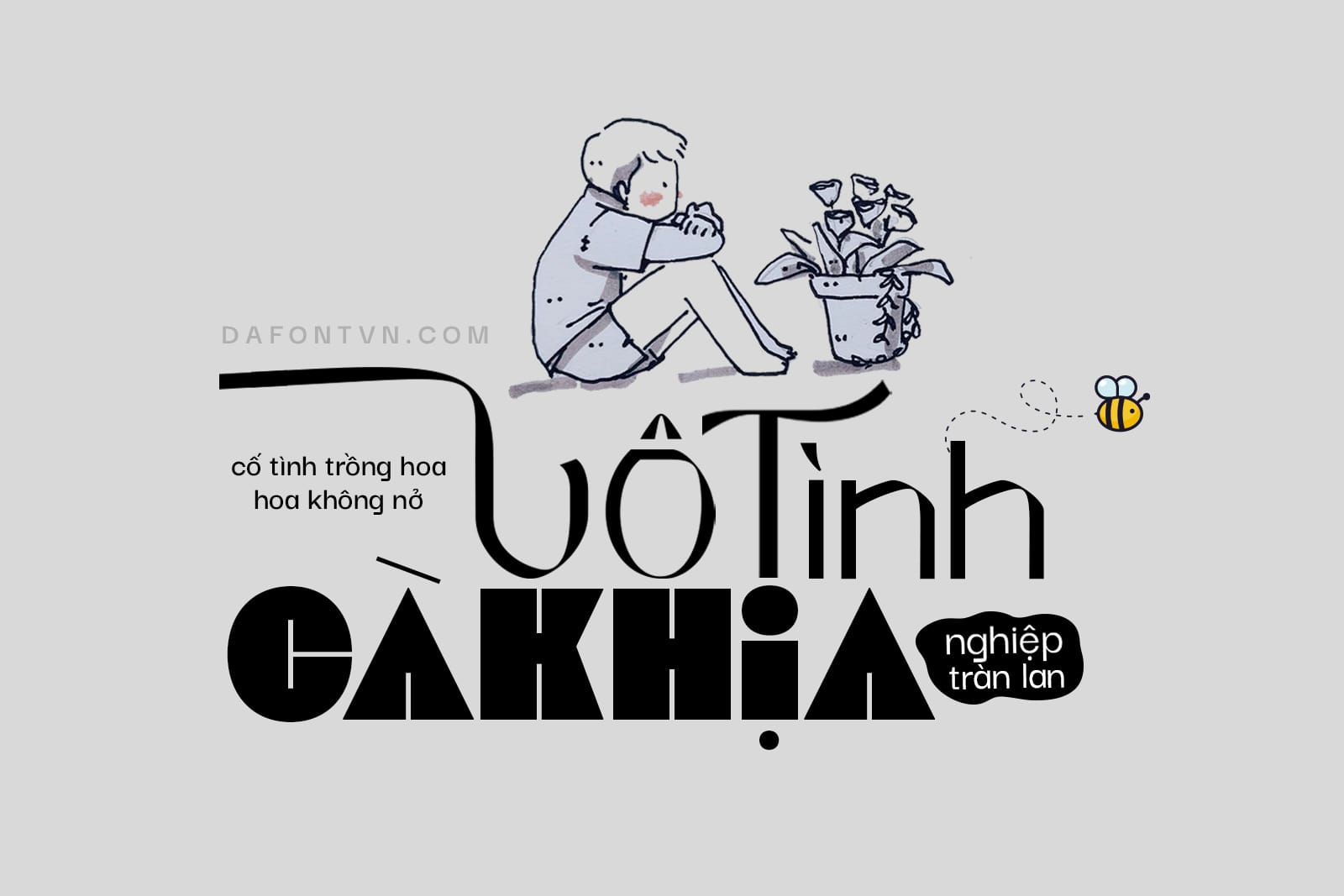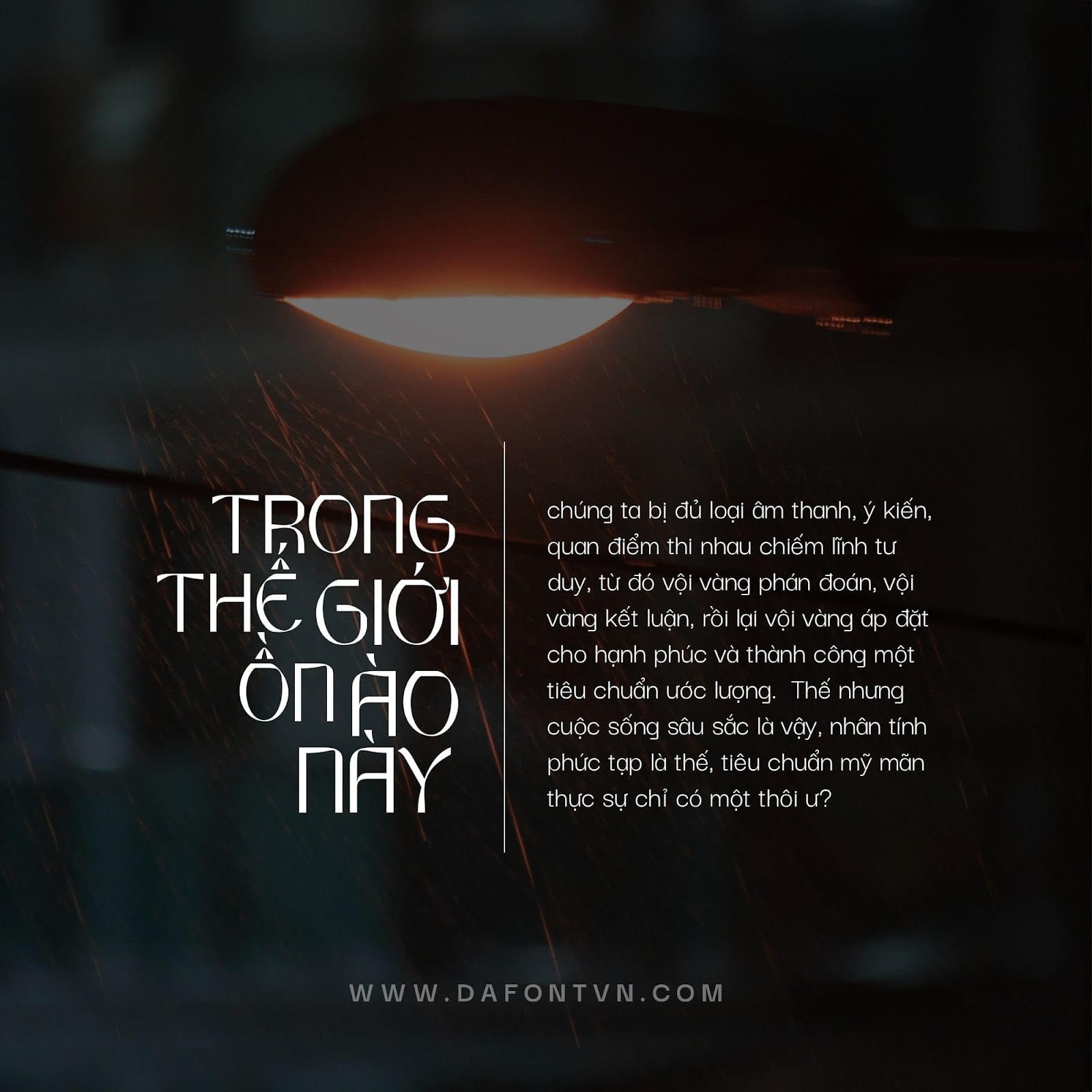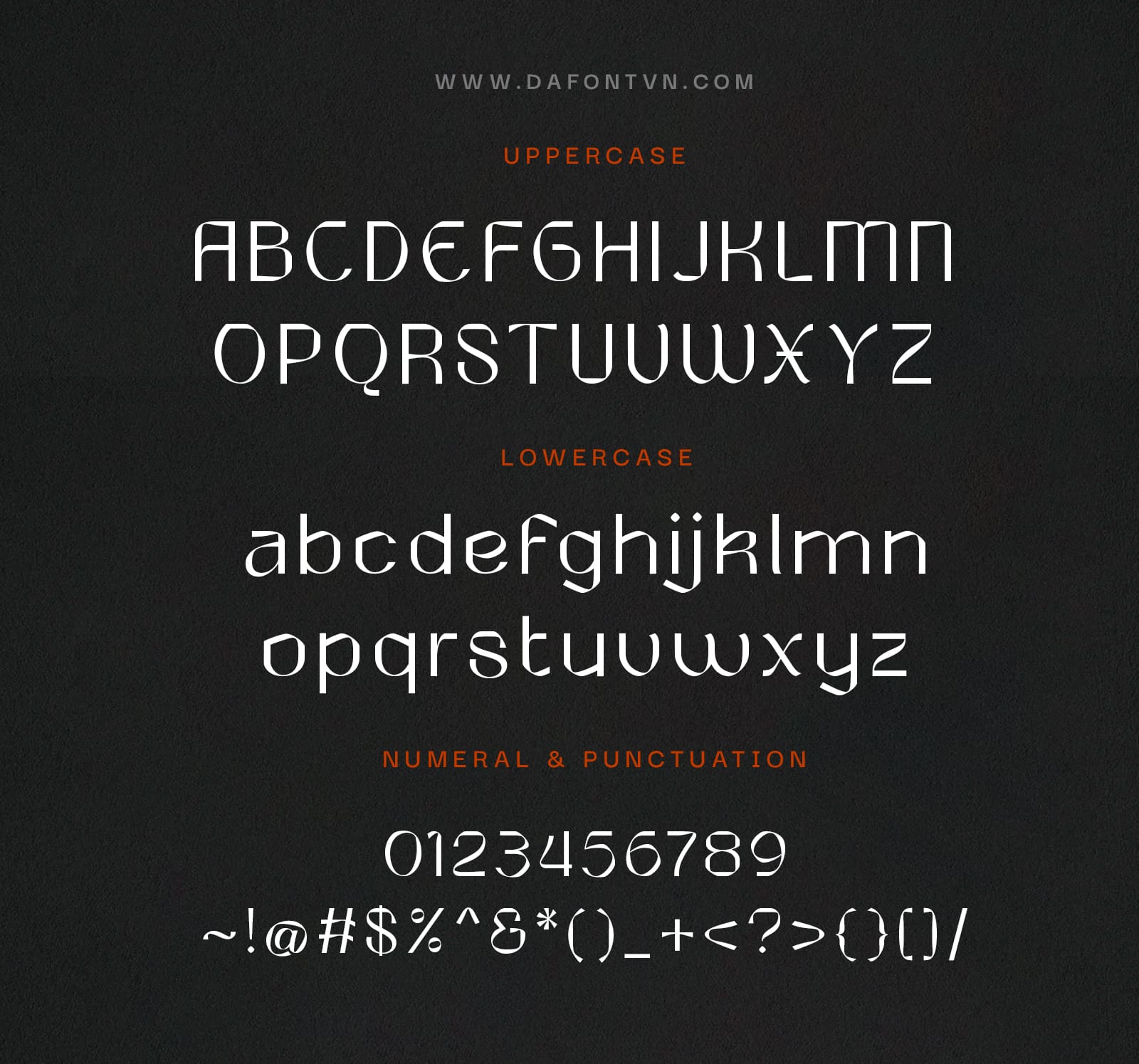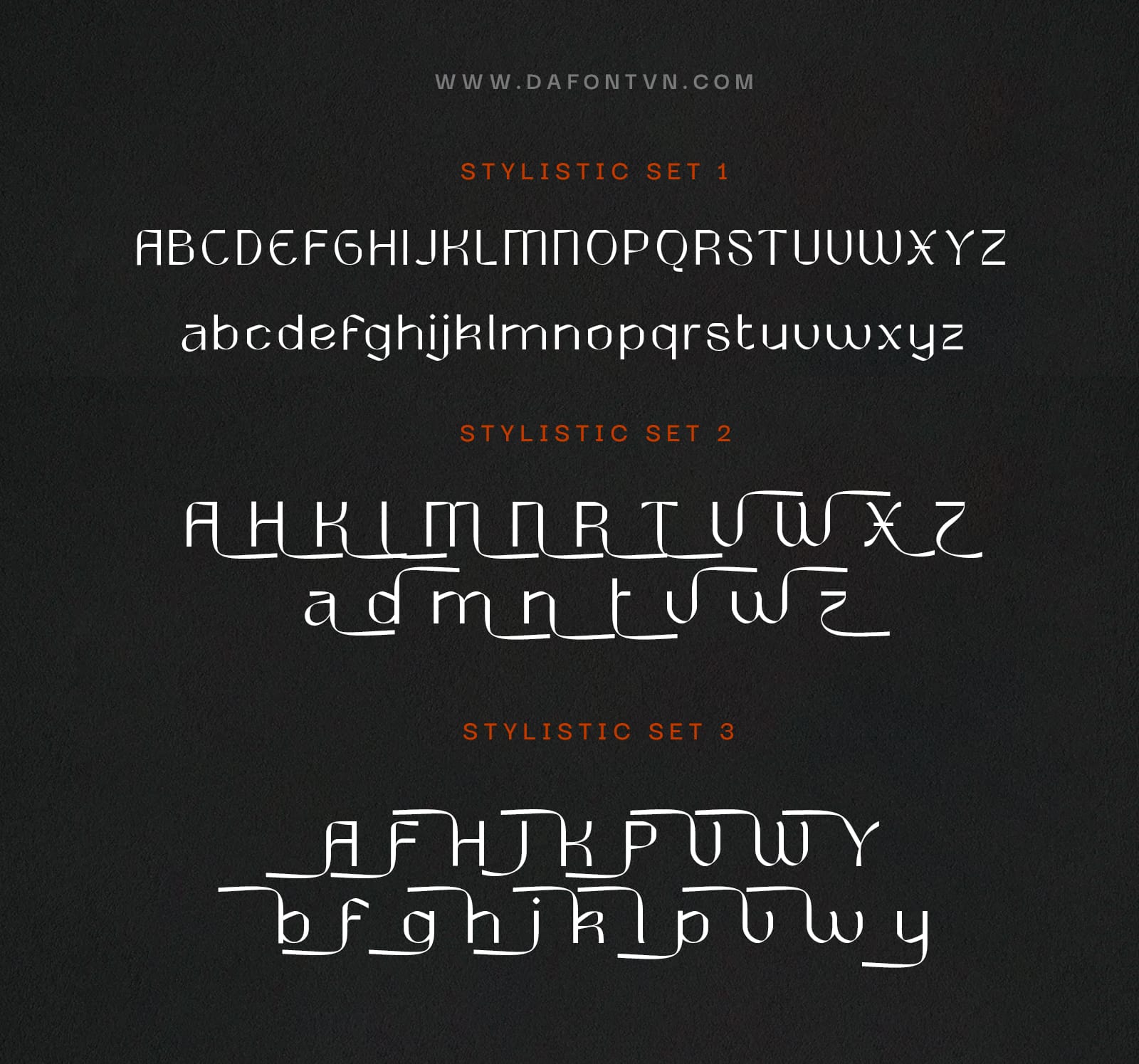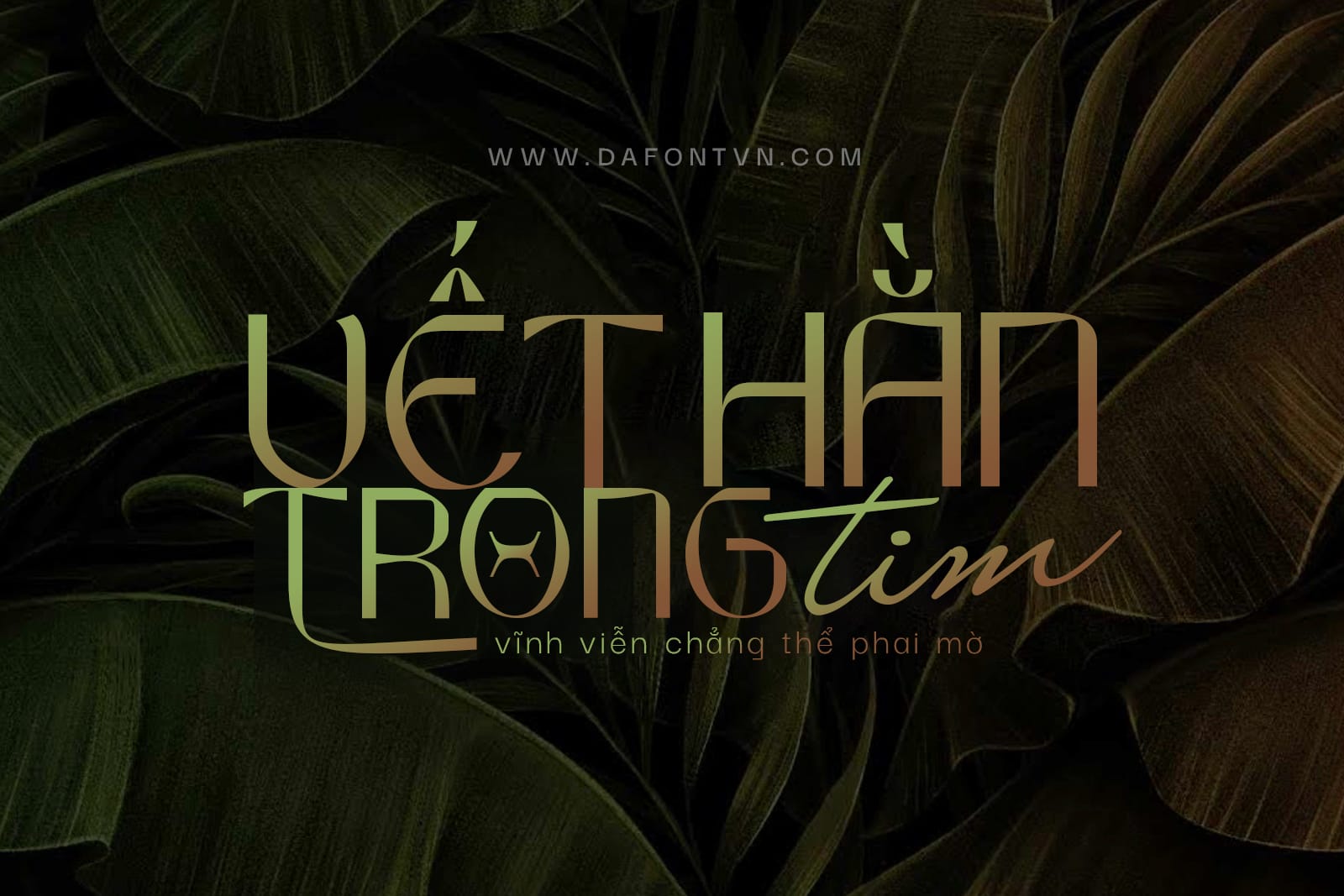
Round Saetan Typeface được tạo ra với kiểu chữ hiện đại mang lại ấn tượng độc đáo vì nó có dạng gấp khúc giống như một dải ruy băng vậy. Phông chữ kèm theo nhiều glyph để bạn lựa chọn tạo ra các thiết kế ấn tượng hơn.
Round Saetan rất dễ áp dụng cho bất ký thiết kế nào, đặc biệt là những thiết kế cần sự hiện đại và mới mẻ, ngoài ra font được mã hóa PUA nên rất dễ sử dụng trong hầu hết các chương trình thiết kế và phi thiết kế.
Round Saetan có 662 glyph với nhiều tùy chọn thay thế độc đáo và thú vị. Thực ra font đã có sẵn dấu nhưng nhiều dấu bị lỗi mình đã sửa lại, kerning, feature và tối ưu lại font cho hoàn chỉnh hơn với dấu tiếng Việt.